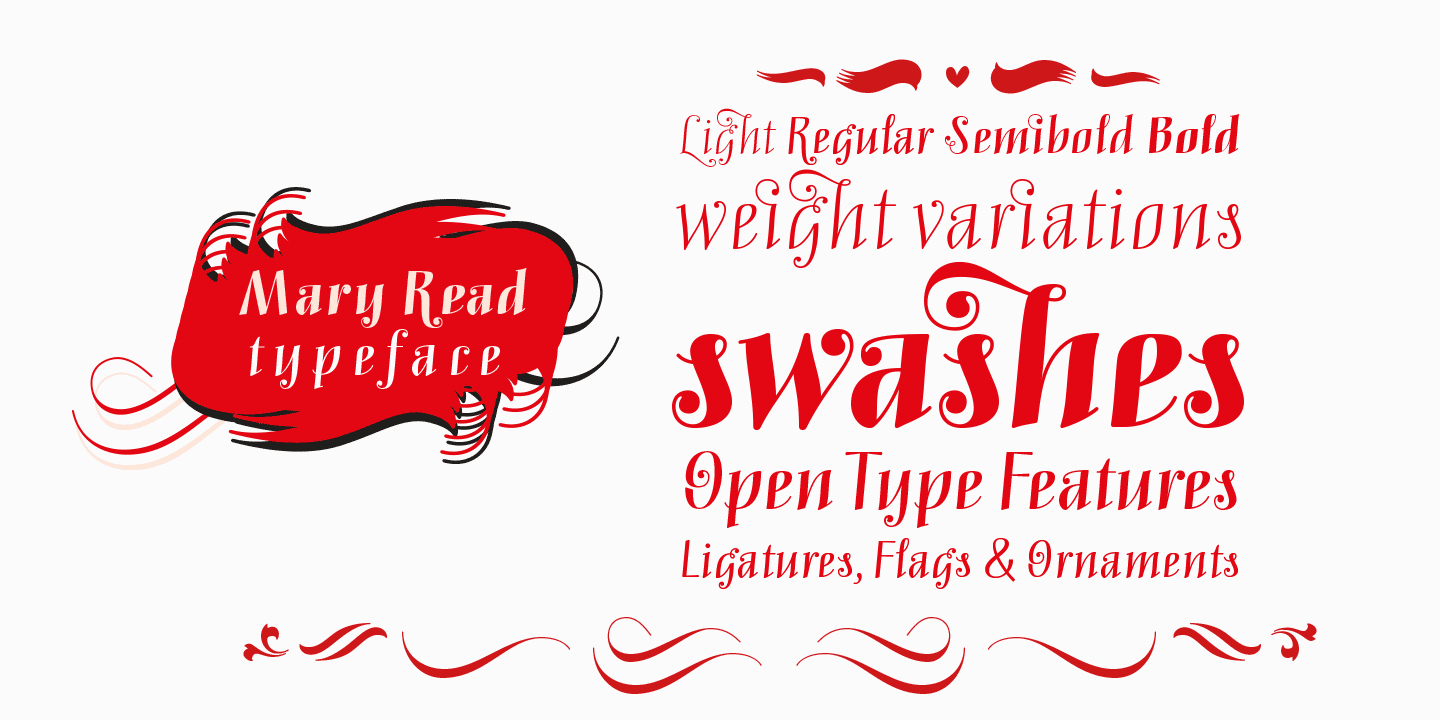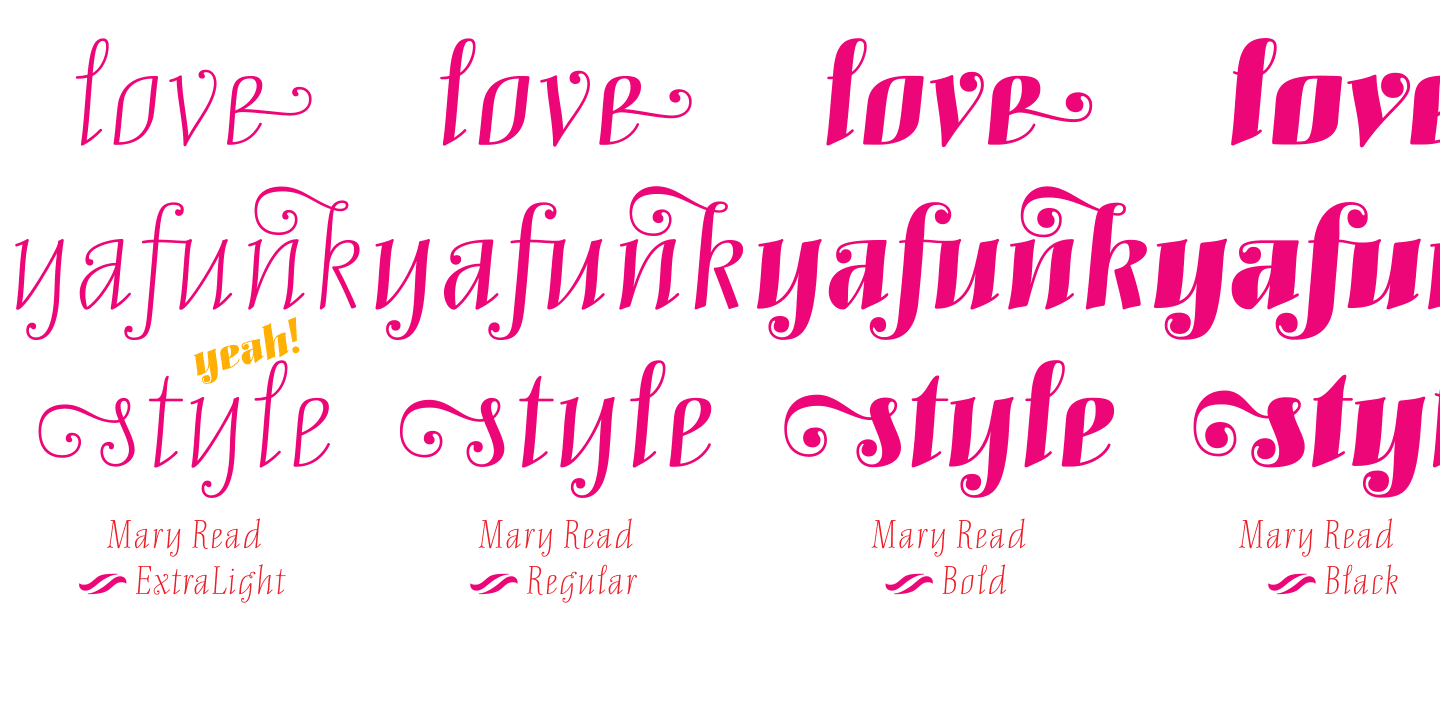
Font-Wiki: Mary Read
• Antiqua dekorativ
Die Mary Read ist eine dekorative, unverbundene Schreibschrift von Melle Diete. Die Schrift liegt in vier Strichstärken mit 374 Glyphen vor. Darin sind Schwungbuchstaben, Alternativzeichen und Piktogramme enthalten.